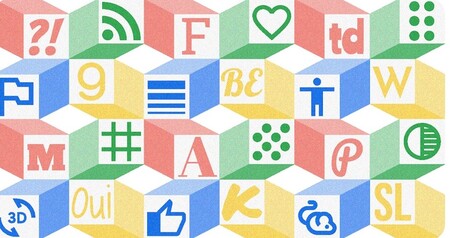
Google Fonts ahora ofrece gratis iconos de código abierto y empieza con los de Material Design
Google Fonts ha incluido los iconos de Material Design a su oferta. Y además ha anunciado su intención, “en el futuro” de añadir iconos de código abierto en general disponibles para sus usuarios. Lo que no ha concretado es cuando van a llegar los nuevos diseños Open Source más allá de la nueva incorporación.
Una gran fuente de recursos para diseñadores gráficos
Para los diseñadores gráficos, Google Fonts ofrece un catálogo gratuito con cientos de fuentes disponibles para el desarrollo de páginas web y de otros recursos. El objetivo es poder acceder a diferentes tipografías a la hora de crear nuevos diseños. Fue lanzada en 2010 por Google como una especie de base de datos online con fuentes de texto open source, con la idea de poder usarlas en millones de páginas web de todo el mundo, y también de que estuvieran disponibles para aplicaciones como Google Docs.
Lo común para las marcas es escoger una fuente y usarla siempre para que visualmente, el usuario o cliente pueda reconocerla por el estilo. Además de estas tipografías, también están los iconos que ahora aumentan con el acuerdo con Material Design.
Un cambio en el logo
Para celebrar la incorporación de los iconos de Material Design, la empresa ha mostrado su nuevo logo. Sobre el nuevo diseño, tal y como explican Tobias Kunisch y SeHee Lee, ambos diseñadores de este proyecto, han explicado que primera vista, el nuevo logotipo puede verse como formas abstractas compuestas con círculos y rectángulos, "pero si se mira más de cerca, se pueden ver varios glifos y formas de iconos mezclados".
Dicen que el objetivo de esta nueva marca visual es proporcionar “una mayor flexibilidad de diseño”.